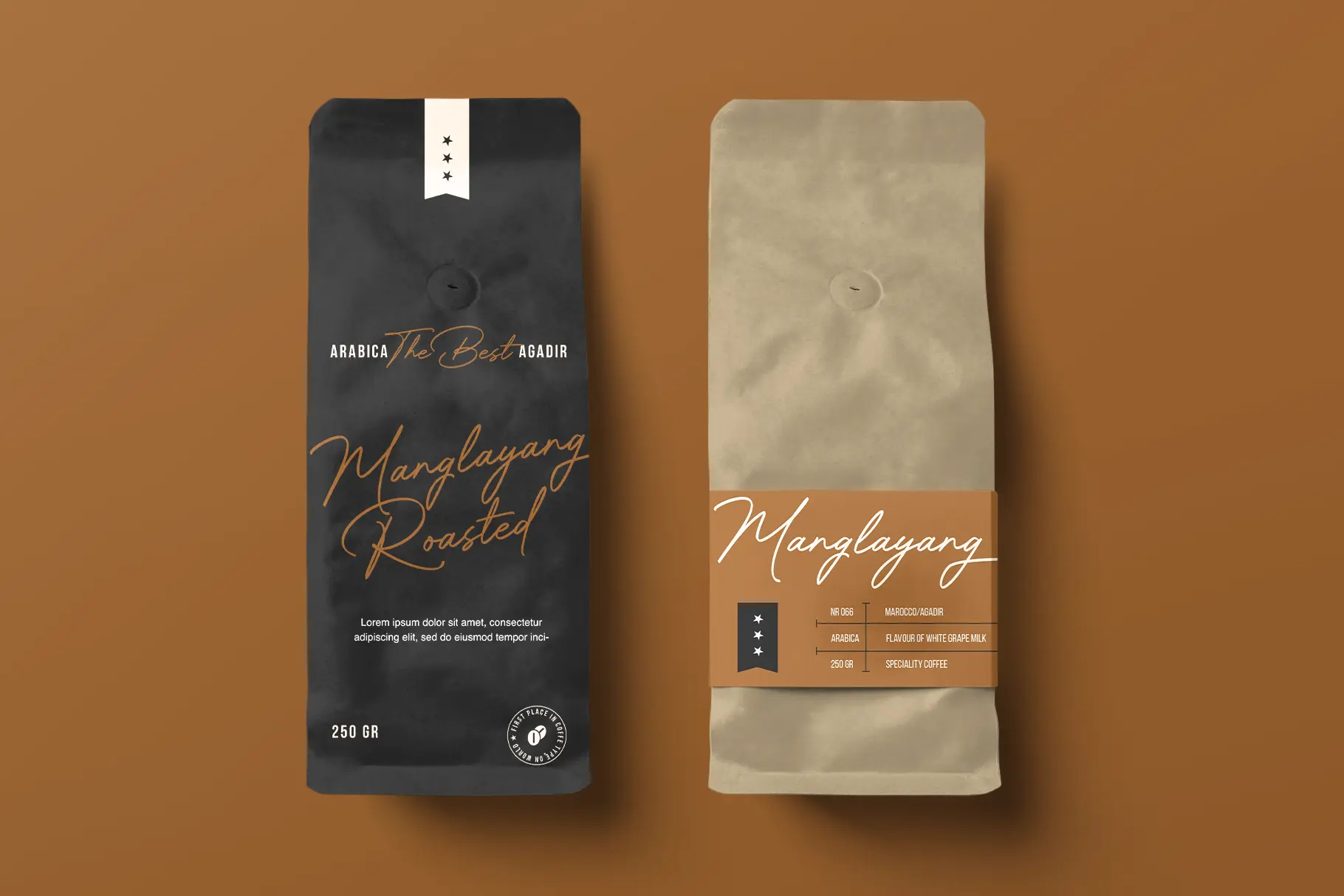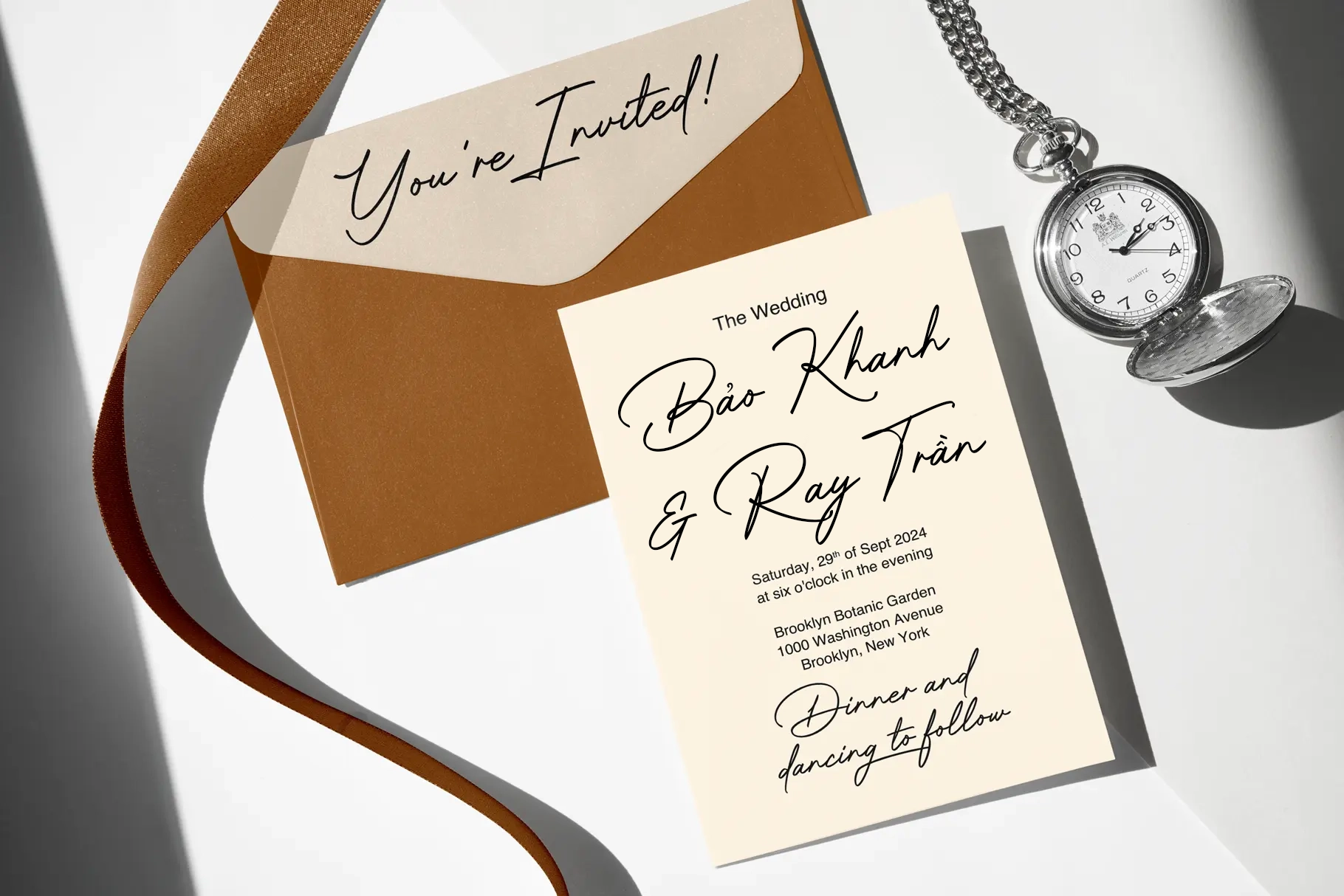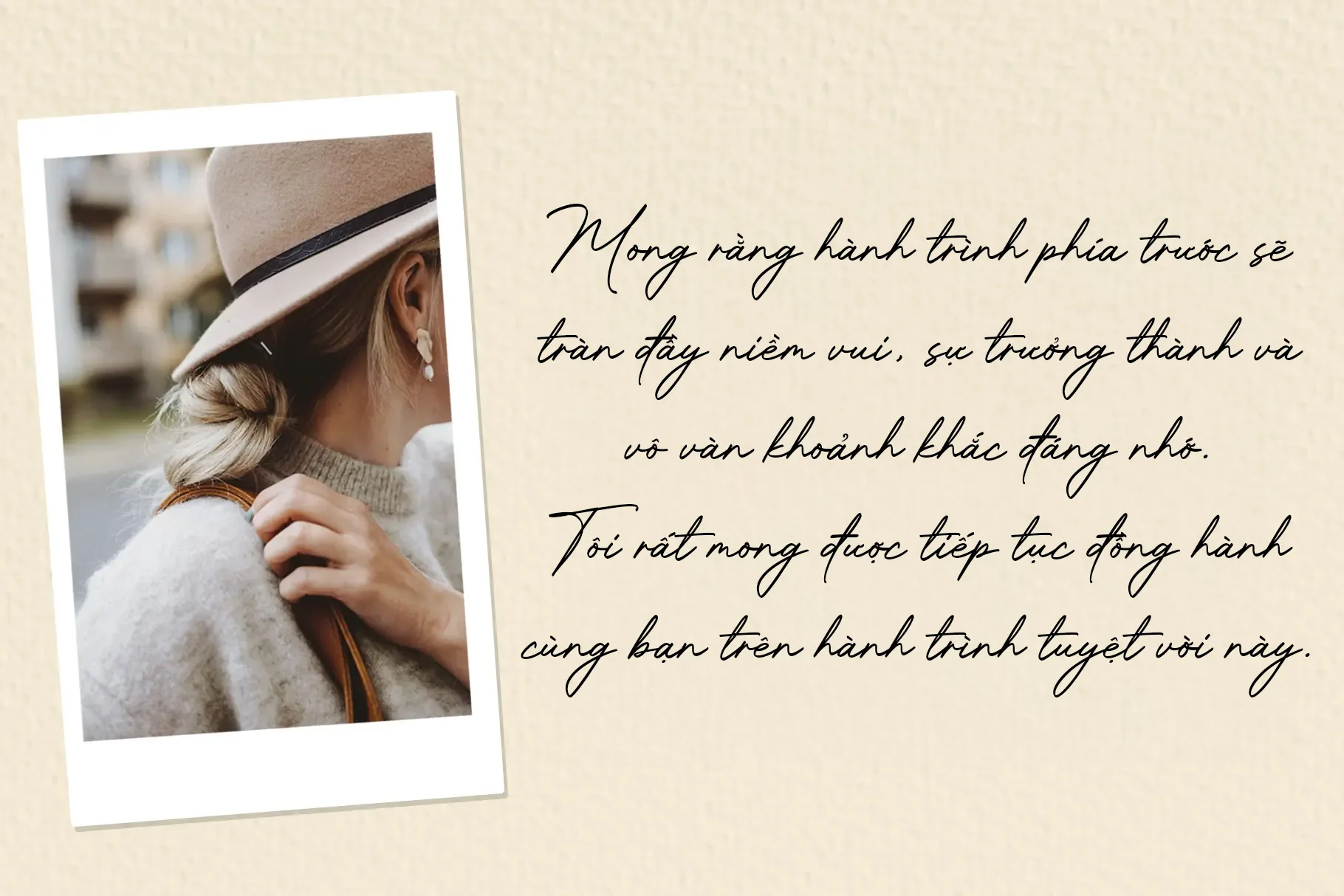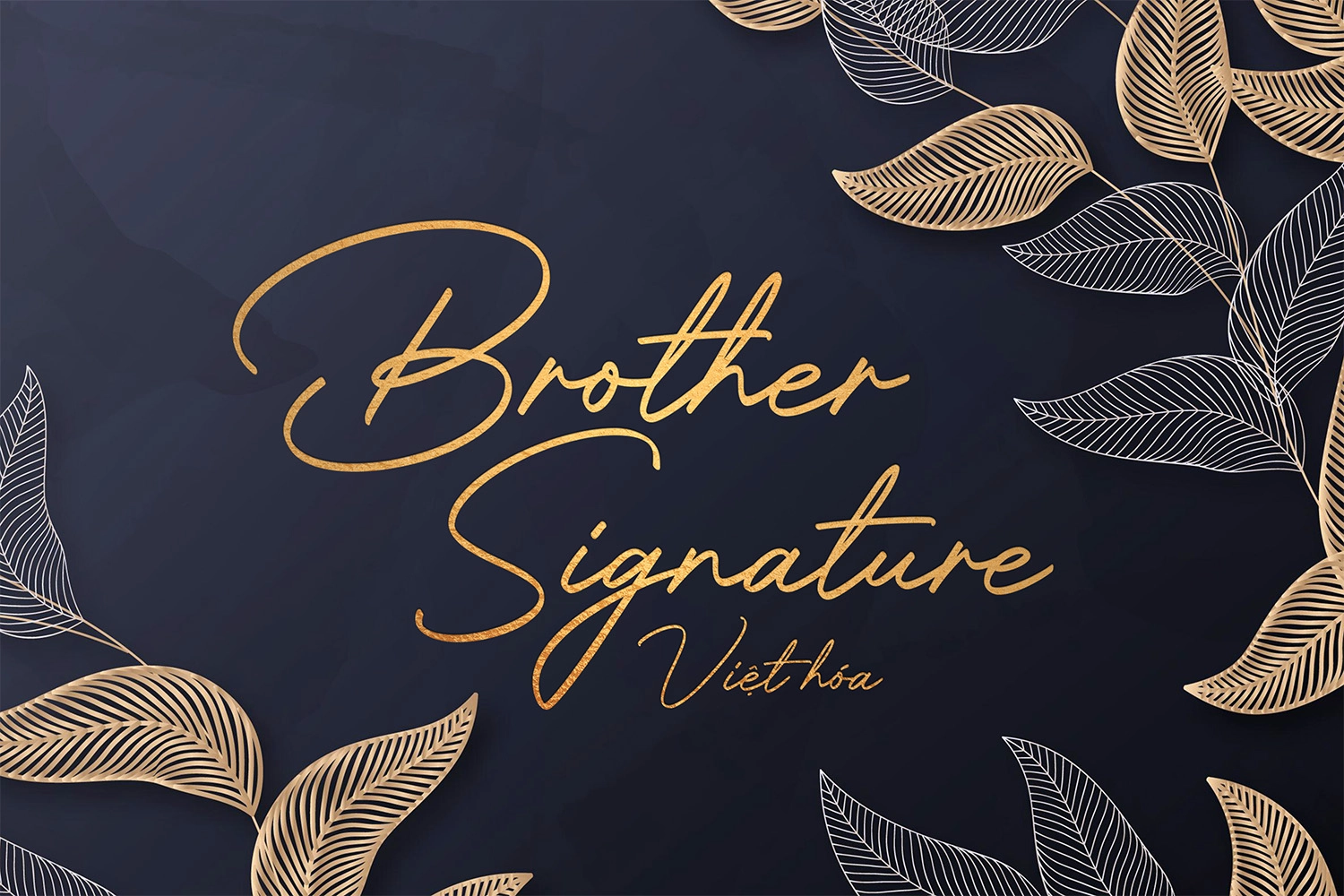
DVN Brother Signature Việt hóa – Font chữ ký đậm chất cool ngầu
DVN Brother Signature là một font chữ ký kiểu calligraphy mang phong cách hiện đại, kết hợp giữa sự mượt mà của đường cong tay viết và chất “cool ngầu” đậm cá tính. Font chữ đã được Việt hóa đầy đủ, font này phù hợp hoàn hảo cho những dự án cần dấu ấn cá nhân như logo, bao bì, tiêu đề, poster thời trang, hoặc chữ ký thương hiệu. Các ký tự được thiết kế linh hoạt với độ nghiêng tự nhiên, tạo cảm giác vừa phóng khoáng vừa thanh lịch. DVN Brother Signature mang đến sự chuyên nghiệp nhưng không kém phần nghệ sĩ – một lựa chọn tuyệt vời cho designer muốn tạo dấu ấn cá nhân rõ nét. Font còn hỗ trợ đầy đủ tiếng Việt, giúp bạn yên tâm ứng dụng trong mọi thiết kế nội dung dành cho thị trường trong nước.